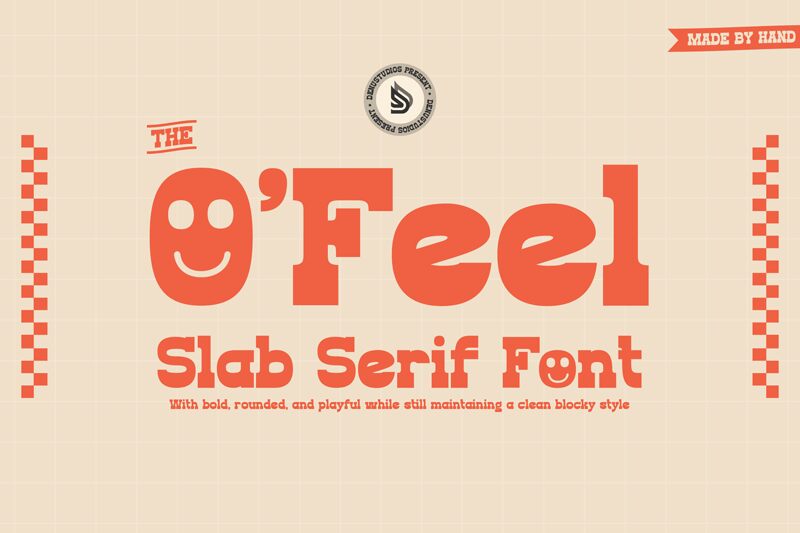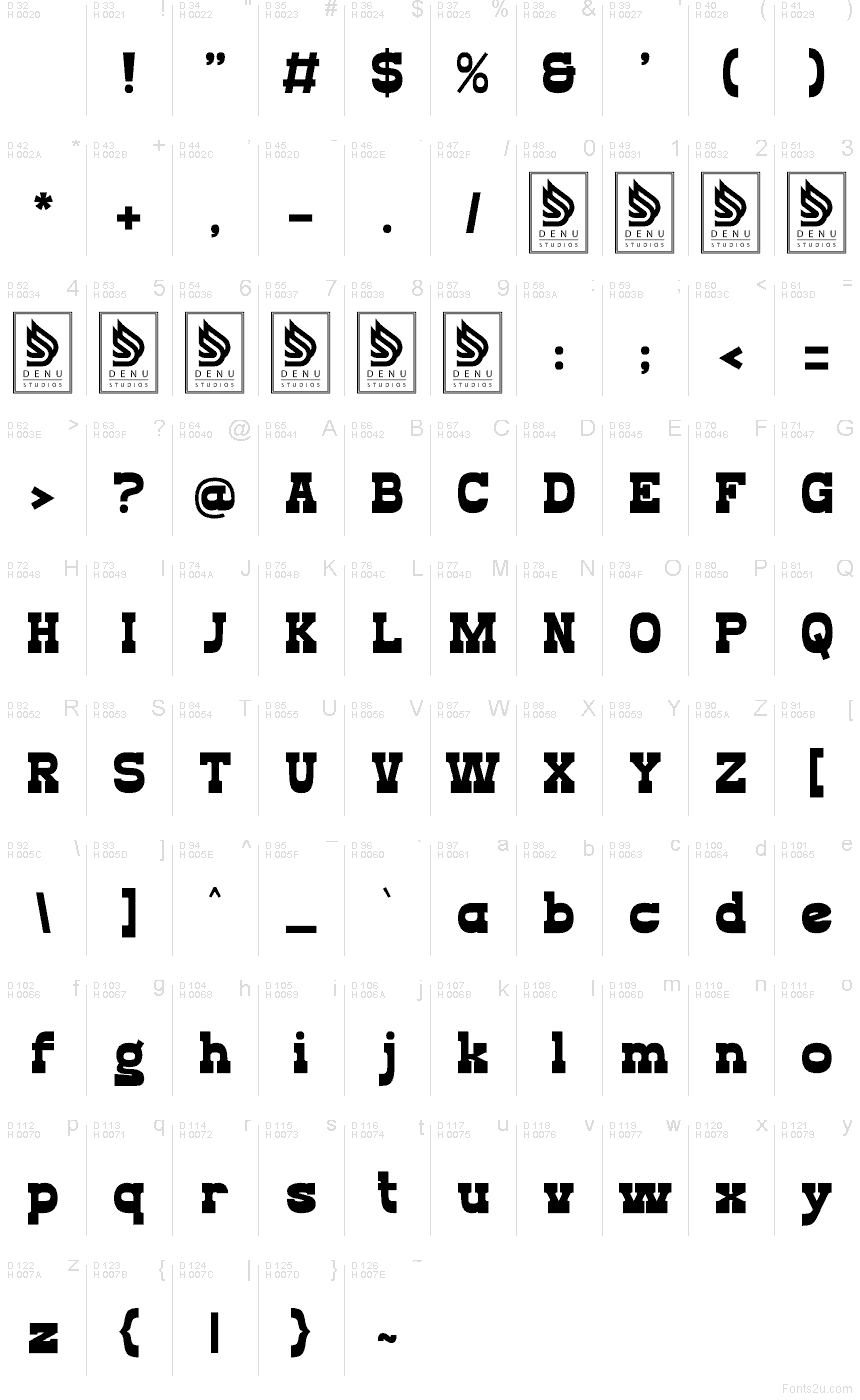
O'Feel od Denustudios je bezplatné westernové titulkové písmo s masivním, ale měkkým charakterem. Písmena působí široce a těžce, se zaoblenými křivkami a blokovými patkami, které písmu dodávají přátelskou atmosféru starého saloonu, bez zbytečné historické upjatosti.
Skvěle se hodí pro branding grilů, obaly řemeslných potravin, plakáty, festivalové letáky a grafiku v retro stylu, kde bezplatné písmo s takovou vahou dokáže samo o sobě vytvořit správný dojem. Hodí se také na obálky, titulky a loga, která potřebují velký a pohodový westernový hlas, protože zaoblení udržují styl hravý, nikoliv přísný.